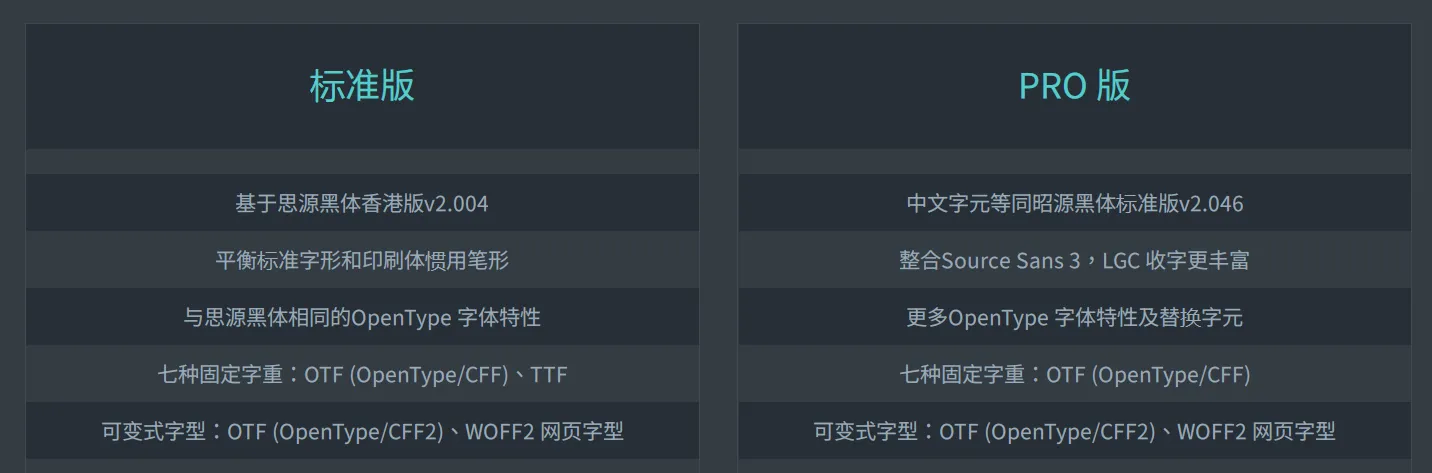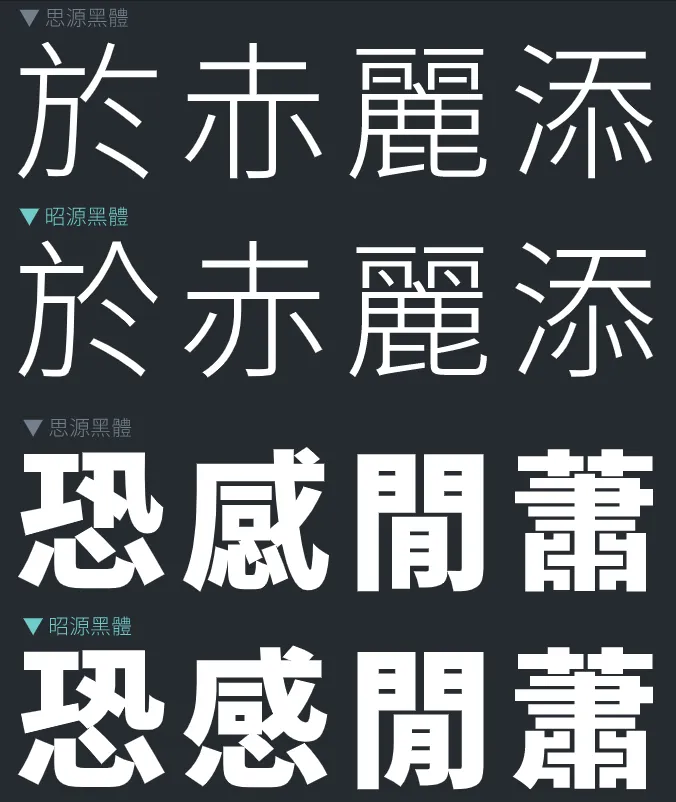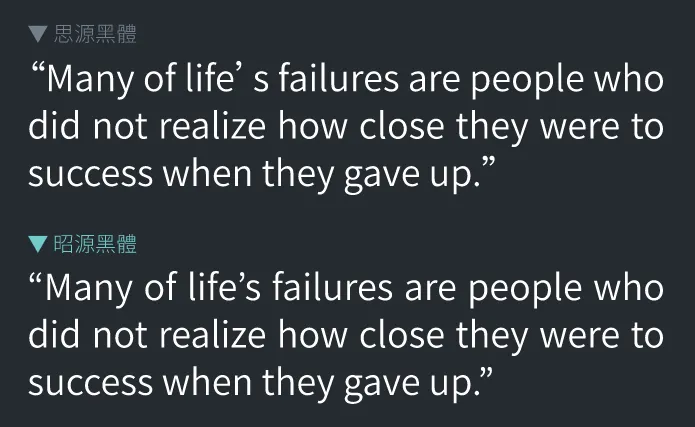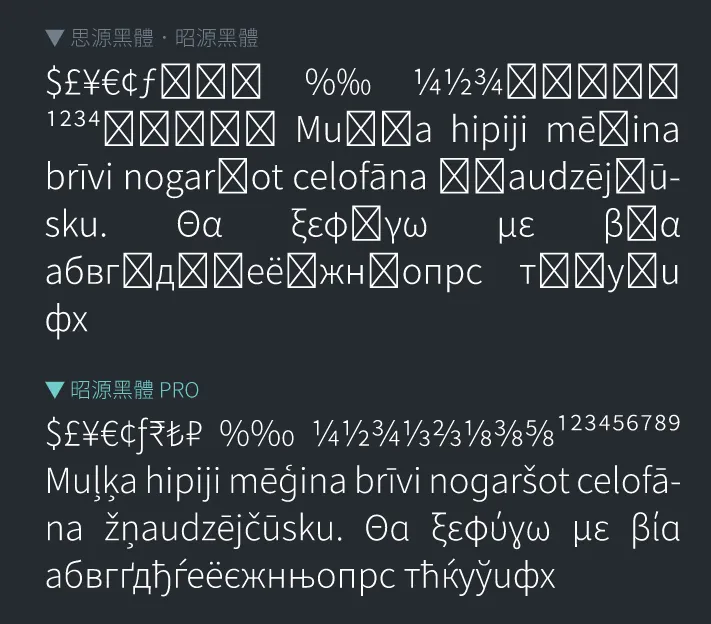
昭源黑體(Chiron Sans HK)以「思源黑體香港版」為基礎,參考繁體中文地區的商用字體作出修改,目標是提供一個兼顧標準字形和印刷體架構的開源字體方案。是一款現代筆形風格,平衡標準字形和印刷體慣用筆形的免費開源黑體字型,專為繁體中文用戶設計,尤其適用於香港用戶。
字重豐富,配搭方:提供豐富字重讓使用者自由選擇是思源黑體的一大特色。為了提供與思源黑體一致的配搭彈性,昭源黑體所有修改或新造字形都做齊七款字重,現在更備有可變式字型格式。
站在巨人肩膊之上,收字繁多:思源黑體是一款泛中日韓(Pan-CJK) 字體,支援的表意文字字符超過四萬,平假片假名、諺文等也一應俱全。昭源黑體除完整保留這些字碼支援外,還收有思源黑體沒有的新造字。
熟悉 ‧ 親切:「思源黑體香港版」是依據《香港電腦漢字參考字形》的字形標準設計。《香港電腦漢字參考字形》以手寫楷書為本,採取「宋體與楷體字形規律一致的總體原則」,其字形規律「並無楷宋之分」,以維持手寫和印刷字形的一致性。在這個原則之下,「參考字形」將好些本來只用於楷書或在以往印刷體(即使是採現代筆形者,無論宋體還是黑體)中極為罕見的部件形態移植到印刷體,其選定的某些筆形或字形結構對一般人來說可能較為陌生,甚至影響辨認。昭源黑體會參考大眾日常生活所見的「事實標準」調整字形。
兼顧印刷體效果:屬於「手寫體」的楷體和屬於「印刷體」的宋、黑字體架構不同,過份強調書寫筆形會令印刷體失去本來端正、整齊的感覺。「昭源黑體」比較著重顯示效果,會按情況選擇,不會盡依「參考字形」。
擇優而從:有些筆畫本來不屬「標準差異」,但思源黑體因為各種原因以「地區差異」將寫法區分。昭源黑體會盡量選擇設計較佳的版本,不拘泥於原來字體對該種筆畫的地區劃分。
額外增加中文新造字:思源黑體支援的中日韓字集本身已經足夠日常使用,幾乎不會有缺字問題。昭源黑體除了加入四個香港會用到但不在HKSCS 字集因而未獲思源黑體收錄的,更額外增加超過1,000 個新造字,使之可以應付以下粵語相關網站的使用(僅限字頭)。
針對繁體中文使用場合調整標點:思源黑體香港版的西文單雙引號('、'、“、”)以全形顯示。由於繁體中文環境多數使用中文款式的單雙引號(「」『』),本字體沿用思源黑體日、韓版做法,將西文單雙引號改為半形,方便中英混排。另一方面,本字體將以下符號改為預設輸出與中文字(而非英文)對齊的版本:U+2E3A(⸺)、U+2E3B(⸻)、U+203C(‼)、U+2047(⁇)、U+2048(⁈)、U+2049(⁉)。由於繁體中文環境不會預設壓縮全形標點符號,本字體將相關的halt、vhal、palt、vpal 指令移除,使用排版軟件時不須額外設定。
更完整的LGC 收字 (PRO 版):昭源黑體Pro 版繼承昭源黑體的所有特點,並進一步整合Source Sans 3 字體,減低使用單套字型時遇到缺字「豆腐」的機會。保留Source Sans 3 的OpenType 功能,提供更豐富的字元變化選擇。